ICON FONT
WHAT THE FONT MAN?!
รูปเล็กไปก็ดูไม่ออก รูปใหญ่ไปก็แตกๆ
ปัญหาของการใช้ icon PNG
WHY MAN?!
ปัญหาของการใช้ icon PNG
ถ้าเราใช้รูปไอคอน 1 รูปต่อ 1 ไฟล์ ก็จะมีปัญหาว่า
ถ้าเรามี 100 ไอคอน ก็ต้องใช้ 100 ไฟล์ การเรียกไฟล์ทีละไฟล์จะทำให้เว็บช้าลง
WHY MAN?!
โหลดช้า แก้ได้
ด้วย CSS Sprite
โหลดช้า แก้ได้
ด้วย CSS Sprite
ICON FONT
ICON FONT?
WHAT IS IT?!
ICON FONT?
ใช้ CSS3 Font Face ในการโหลดไฟล์ฟ้อนต์เข้ามาใช้
WHAT IS IT?!
ICON FONT?
T
เหมือนใส่ตัวหนังสือ 1 ตัว
สามารถใช้ CSS ตกแต่งได้ตามสะดวก
WHAT IS IT?!
FONT AWESOME
WHAT A PRETTY THING!
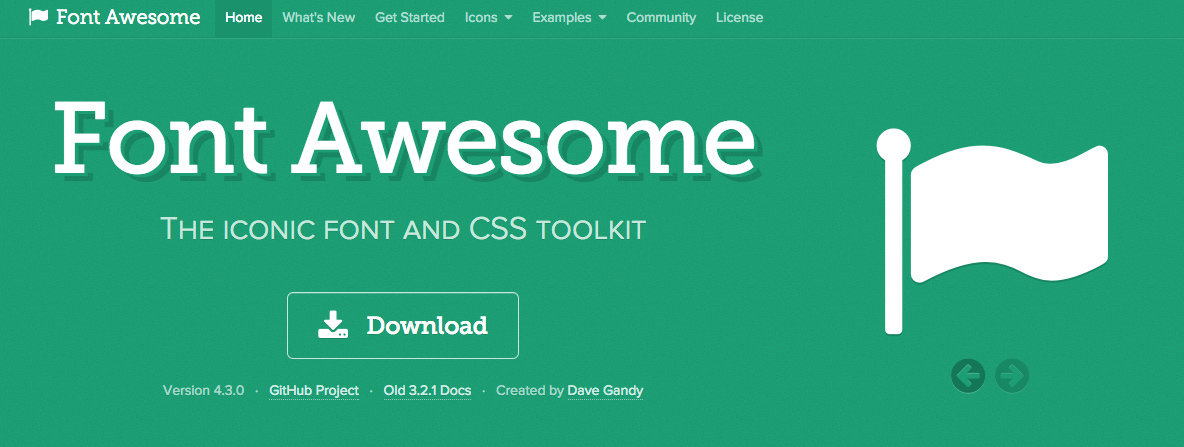
● อยู่ใน Bootstrap ตั้งแต่ V2.x
● มีไอคอนทั้งหมด 300+ ให้เลือกใช้ และยังเพิ่มขึ้นเรื่อยๆ
● ซัพพอร์ทตั้งแต่ IE7 ขึ้นไป
1 ดูไอคอนทั้งหมดที่อยู่ใน หน้ารวม Icon ของ Font Awesome
เลือกไอคอนที่อยากใช้มา 1 ตัว
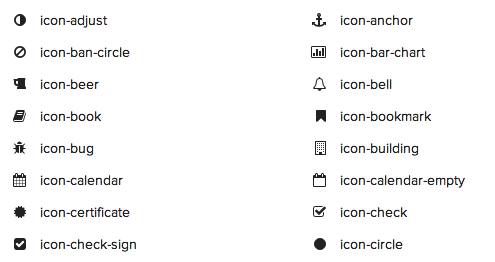
2 ดูชื่อ class ที่ด้านล่างรูปไอคอน
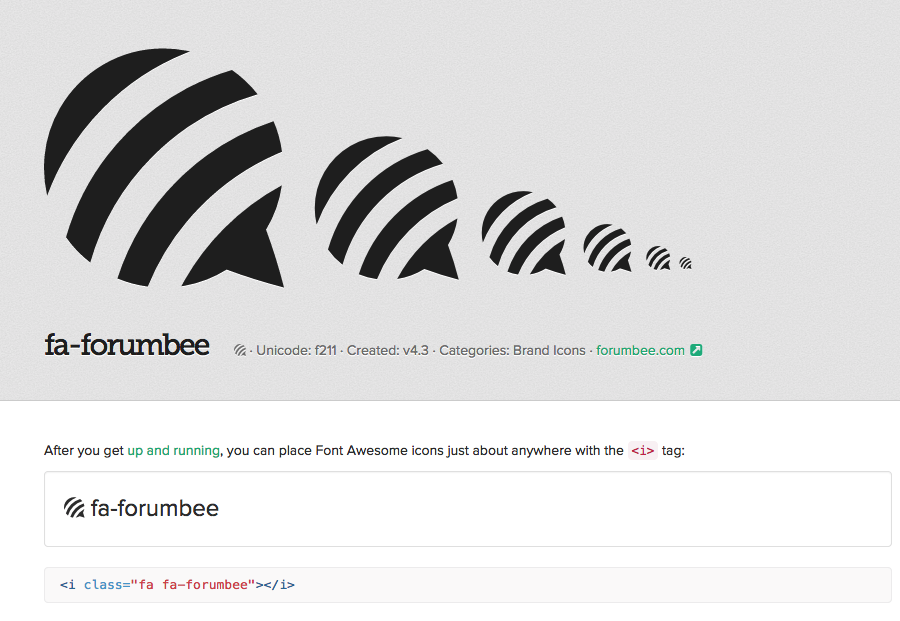
ในตัวอย่างเขียนว่า fa-forumbee
จะเห็นว่าต้องมีคลาส fa ด้วยทุกครั้งเพื่อบอกว่าจะใช้ Font Awesome
3 เรียกใช้โดยใส่โค้ดตามนี้
fa-lg, fa-2x, fa-3x, fa-4x, fa-5x เข้าไป (ไล่จากใหญ่น้อย ไปถึงใหญ่มาก)
4 เราสามารถใช้ไอคอนขนาดใหญ่กว่าปกติก็ได้
ด้วยการเพิ่มคลาส
ทำใช้เองก็ได้ ดี๊ย์ดีย์
ICON FONT